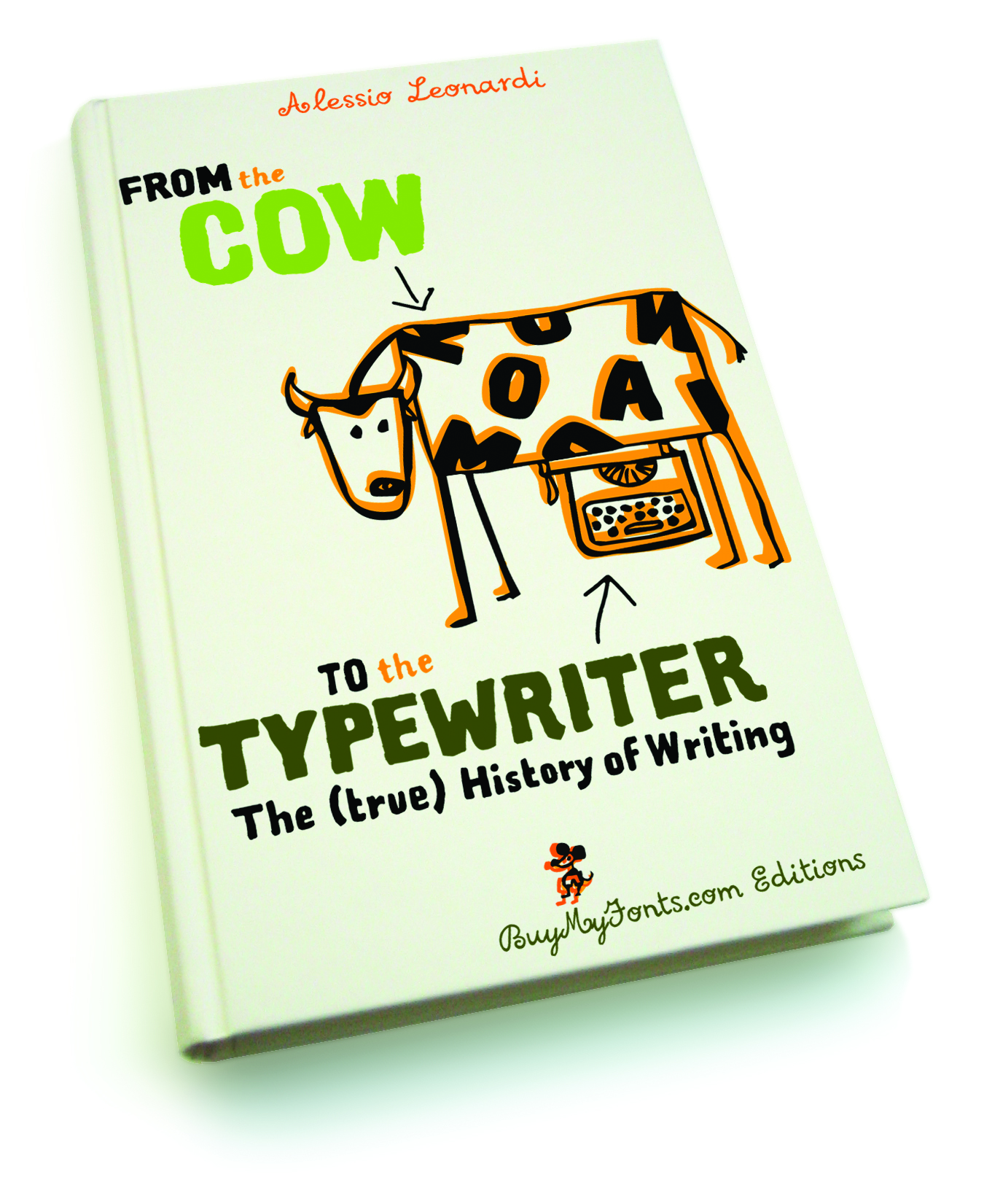
Sobre la historia de la escritura hay mucho material bibliográfico muy sesudo, por ejemplo, el de Harald Haarmann o el de Louis-Jean Calvet, con un alto grado de erudición y profusamente detallados, a juicio de los críticos. Sin embargo para aquellos que no necesitan tanta erudición, Alessio Leonardi ha publicado un manual muy divulgativo, fácil de leer y que hace un repaso —en tono jocoso, eso si— a toda la historia de la escritura, desde sus antepasados, las vacas sumerias, hasta las máquinas de escribir. Lectura agradable en la lengua en la que Carlos V decía hablar con sus caballos, pero no por ello menos exacta. Un regalo ideal para los más jóvenes de la casa y que como premio, viene con un dibujo del propio Alessio en el sobre de envío, además de algunos otros regalos tipográficos. Lo podeís pedir aquí, pero si no os funciona el enlace, mandádle un mail y os contesta enseguida.